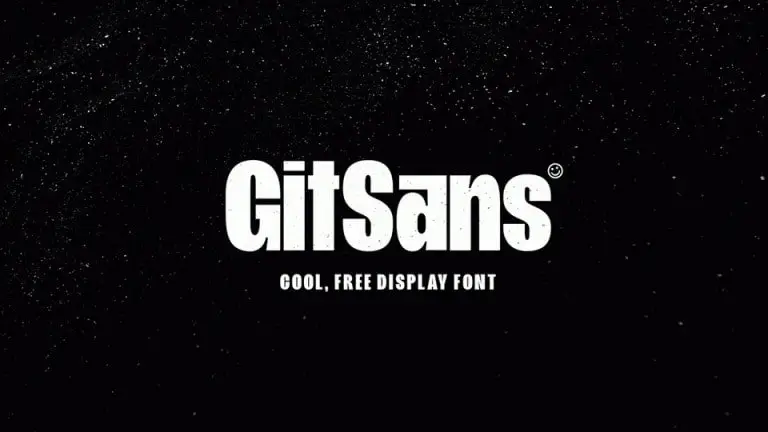
A GitSans Sans Serif Font é uma nova adição à família de tipos modernos e elegantes do setor digital. Criada pelo designer Michał Mareczko através de 99designs, essa fonte sans-serif se destaca por seu uso fácil e versátil em diversos campos da comunicação visual. Perfeita para títulos robustos e design editorial agressivo, GitSans apresenta um visual contemporâneo que é ideal tanto para logos quanto para criações de capa impactantes. Além disso, sua utilização simplifica o processo de impressão digital ou papel. Os designers e gráficos que buscam uma fonte clara e minimalista, mas ainda com um toque moderno, encontrarão aqui a solução perfeita. Seja você designer web, editor de revistas ou produtor de conteúdo online, a GitSans é uma ótima escolha para dar vida à sua ideia, garantindo um visual atraente e eficaz em qualquer projeto.